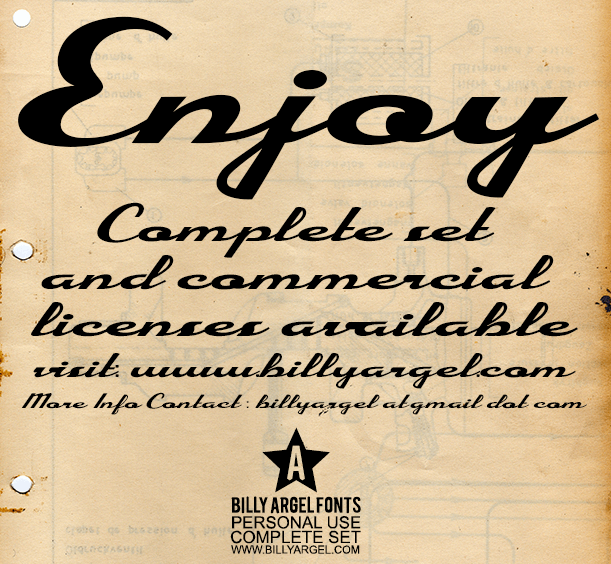
Enjoy Font – Download Grátis
A fonte Enjoy Font é uma escolha perfeita para quem deseja adicionar um toque único e pessoal a seus trabalhos digitais. Esta typewriter font foi projetada pelo designer Hamilton, trazendo à tona um estilo retro e autêntico, ideal para aplicar em designs de boletos bancários, relatórios históricos ou até mesmo cards de fidelidade. A fonte Enjoy Font é especialmente interessante por ser gratuita e livre apenas para uso pessoal, embora os comerciais e as licenças completas estejam disponíveis no site @billyargel.com. Para mais informações ou para entrar em contato com o designer, visite www.billyargel.com e siga-nos no Facebook através de www.facebook.com/billyargelfonts.